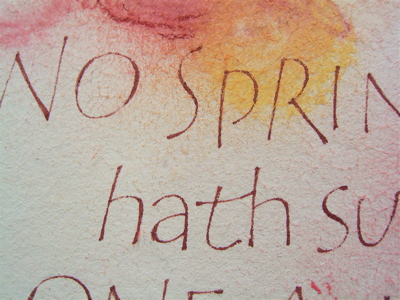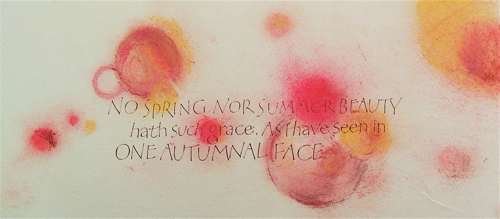
麻紙に書く
隔週水曜日の午後に行なわれている羽賀先生によるアート&ドローイングクラス。夏休み前にこの麻紙の下地を作りました。
忙しさにかまけて放ったらかしでしたが、ようやく文字を入れてみようと思い立ちました。
和紙の良さ(表面のけばけば感、柔らかさ)はそのままにして、文字をきれいに書けるようにするために、下地処理として水で薄めた白のアクリル絵の具を繰り返し塗りました。その後ソフトパステル。
このようにパステルを使う場合は、紙の表面がベタっとしてしまうことは極力避けたいわけです。
以前ジェッソでやってみたことがありましたが、それはそれでざらっと感が少し残った下地が出来ましたが、フワフワ感はまったくなくなってしまいました。
パステルの顔料がたくさんのっている所はさすがにガッシュを吸い込んでしまって書きづらかったですが、それ以外は、おおっ!書けますね。
表面のけばけば感が強いので、スピードのあるカーシブの文字は難しいかもしれませんが、そうでなければいろいろ使えそうですよ!
きちんと水張りしてから下地はつくると良いと思います。
クラスの中ではアクリル絵の具ではなく漆喰もいつか試す予定になっていて楽しみです。